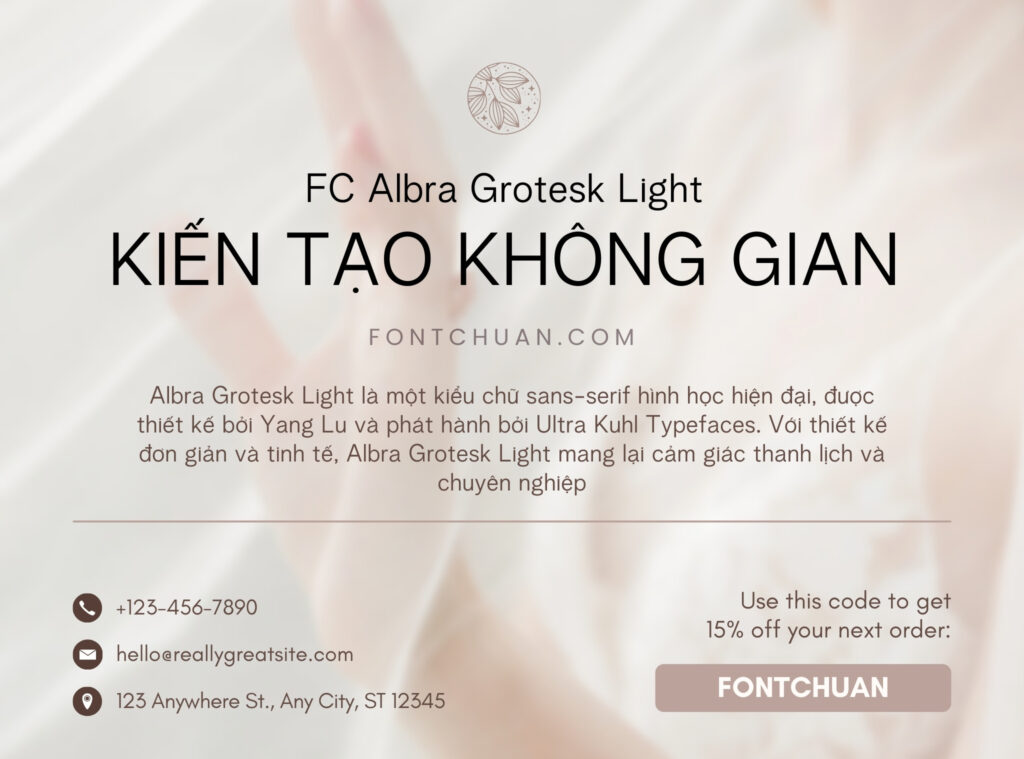
Albra Grotesk Light là một kiểu chữ sans-serif hình học hiện đại, được thiết kế bởi Yang Lu và phát hành bởi Ultra Kuhl Typefaces. Font này hỗ trợ đa ngôn ngữ, bao gồm tiếng Việt, tiếng Anh và nhiều ngôn ngữ Latin khác, mở rộng khả năng ứng dụng trong các dự án quốc tế. Bên cạnh các ứng dụng chuyên nghiệp, Albra Grotesk Light cũng có thể được sử dụng như một Font Lễ hội để tạo điểm nhấn sinh động, vui tươi cho các poster, banner hoặc ấn phẩm sự kiện đặc biệt.
Với cấu trúc chữ cân đối, độ dày nhẹ và thiết kế tinh tế, Albra Grotesk Light phù hợp cho các thiết kế yêu cầu sự sang trọng và hiện đại. Đặc biệt, font này thích hợp cho các ngành nghề như quảng cáo, thiết kế thương hiệu và lĩnh vực biên tập, nơi cần sự kết hợp giữa thẩm mỹ cao và chức năng truyền tải thông điệp.